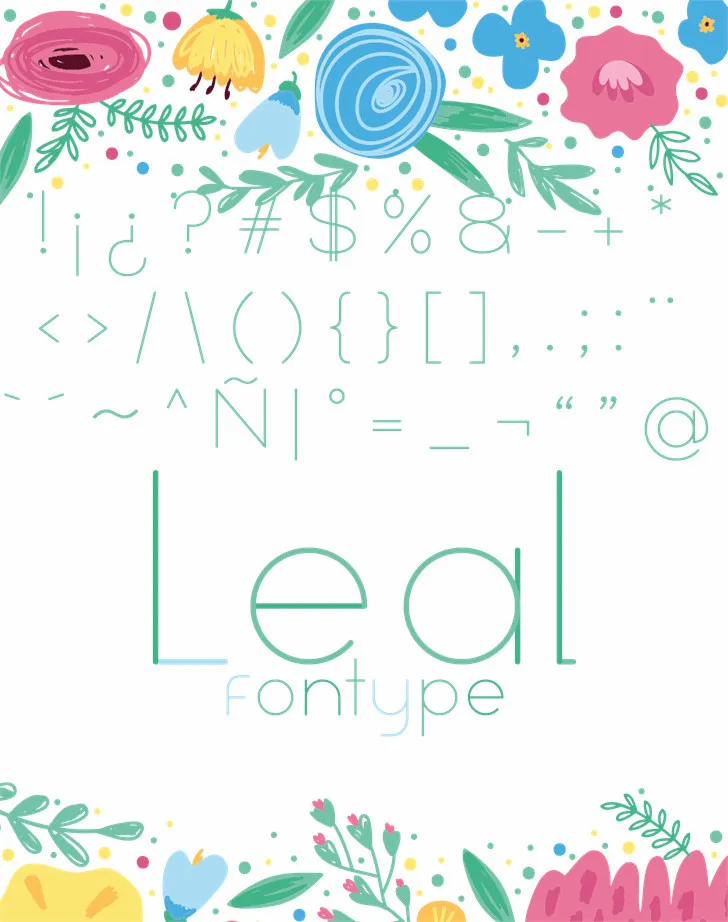
A Leal Font é uma elegante escolha para designers digitais que valorizam simplicidade e modernidade. Desenvolvida por Hamilton, essa fonte sans-serif traz um design fluido e intuitivo, ideal tanto para textos de página web quanto para aplicações móveis. Seu caráter limpo e minimalista é perfeito para criar uma aparência clean e profissional em qualquer projeto digital. Com a capacidade de se adaptar facilmente aos diferentes tamanhos de fonte e ao longo da linha, a Leal Font é uma ótima escolha para quem busca um equilíbrio entre modernidade e funcionalidade. Se você está procurando por uma opção clean que possa complementar projetos web sem comprometer o estilo contemporâneo ou deseja um elemento visual que ajude a estabelecer uma comunicação digital forte, então Leal é definitivamente para você. Para acesso direto aos caracteres comerciais e ao restante da fonte, visite http://ljdesignstudios.es.tl/Leal.htm. Para dúvidas adicionais ou pedido de uso comercial, entre em contato através do